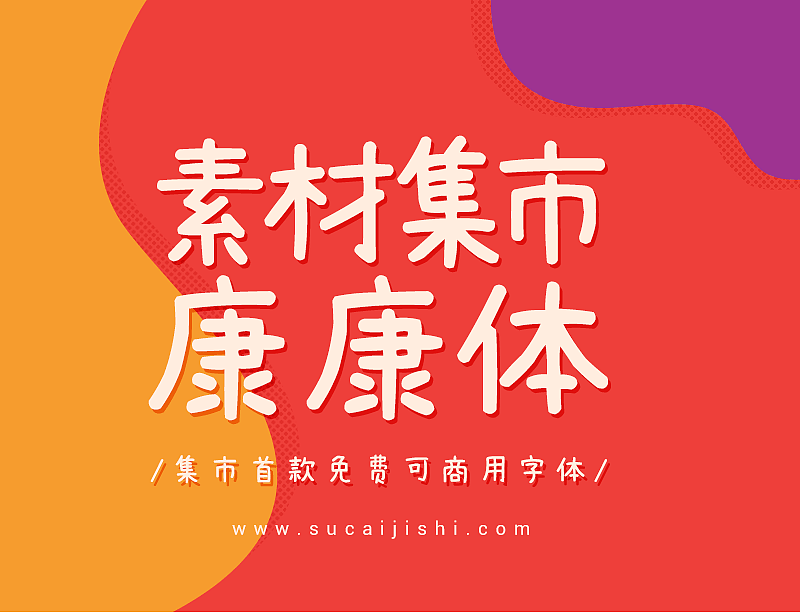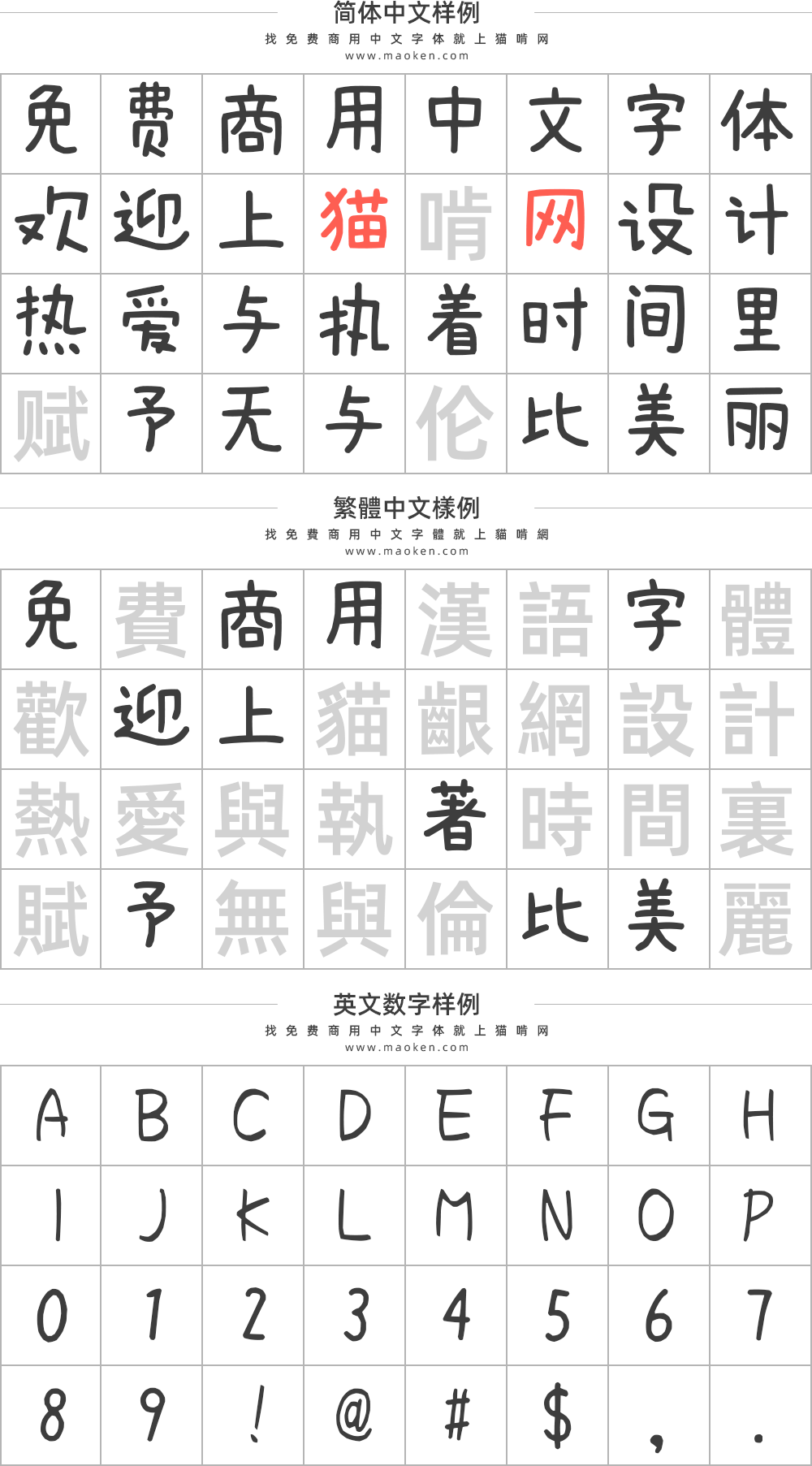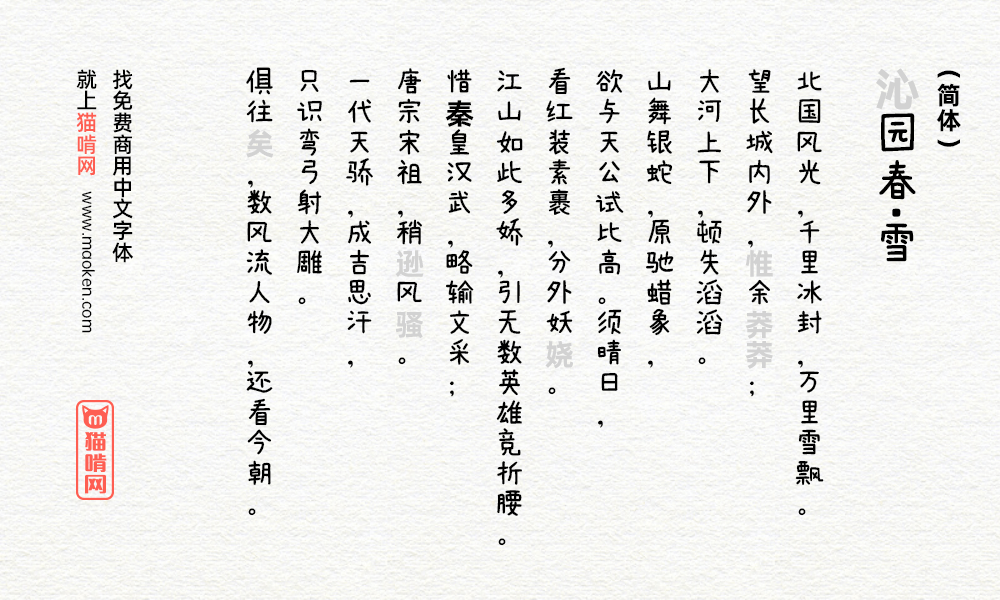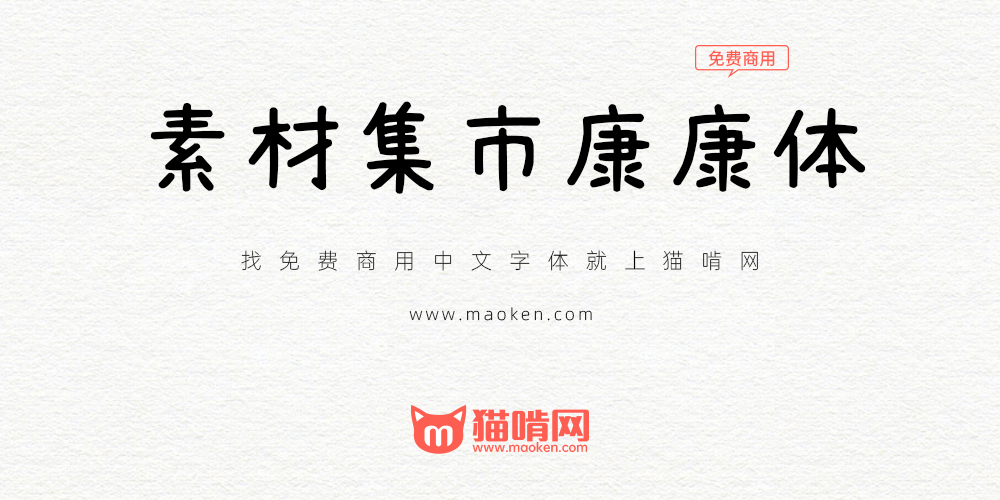
素材集市康康体是一款萌系可爱手写风格中文字体,时隔一年终于迎来更新。1.0版是在2020初疫情隔离期间完成,发布至今获得各界朋友肯定。
2.0版由字集团队成员时光羊独立完成,用了3个月时间增补3500+字,目前字库汉字和字符共计6150个,无论是个人还是企业都可以免费商用。
3.0版本由字集团队成员 时光羊 独立完成,用了近6个月时间,在1.0版基础上增加5131个字补齐GB2312-80编码字库,目前汉字和字符共计7754个。
我前几天刚刷到一张用这个字体的图片,我查了一下才知道是这个字体,结果回来一看,炸锅了!
听说这字体乃是盗用一日本字体而来(免费商用但并不开源,也不允许二次修改),贸贸然使用恐有侵权风险,慎用
如果是这样的话,就是版权诈骗(不可信的“免费商用”声明)。
原版可以商业使用,但是部分受限,然后这个字体目前还在法律灰色地带。每个原作署名很可能违反了原作的条款。
所以,这不再只是存疑,是违反许可协议!
APJapanesefont 的增补字体,有些字没改成简中写法,比如与。
素材集市康康体3.0几点疑问与建议: 1. 官网未标示是OFL协议。是否属实? 2. 与 字是典型的日文汉字写法,看着有些怪怪的。 是否有微调的计划? 3. 样张的 虎 字,宝盖无右钩, 总感觉有笔画被遮住了。
我写错了~~已改左。其余两个问题要@时光羊
有微调计划,反应的问题会在后续的版本中改进
3. 如果可以, 建议后续可以考虑补齐完整至 GB2312-80 编码的 6763个汉字,形成一套更正规的中文字体.
3.0会解决所有问题
这字体有问题!第一、这字体还有一些缺字,第二有些字体和“方正喵鸣体”有高度相似的字!应该下载或者移到争议字体!
此字體修改自あんずもじ!
這個字體來自:あんずもじ